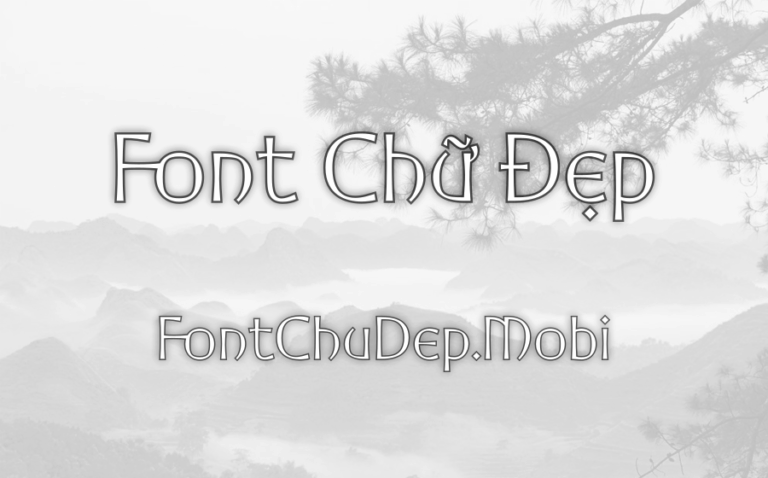
Font UVN Thời Đại 1, do nhà thiết kế tài năng Tom Trương ra mắt vào năm 2001, thực sự là một kiệt tác trong thế giới phông chữ sans-serif. Những đường nét tinh tế, rõ ràng và đầy thanh lịch của nó không chỉ đáp ứng nhu cầu dễ đọc mà còn mang đến vẻ đẹp hiện đại, cuốn hút. Là một người đam mê thiết kế, tôi hoàn toàn bị chinh phục bởi sự hỗ trợ toàn diện của UVN Thời Đại 1 với các ký tự tiếng Việt, làm cho nó trở thành lựa chọn lý tưởng cho các dự án liên quan đến văn hóa bản địa.
Không chỉ nổi bật với thiết kế gọn gàng và tối giản, UVN Thời Đại 1 còn có khả năng ứng dụng rộng rãi trong nhiều lĩnh vực khác nhau. Từ việc thể hiện sức mạnh trong các tiêu đề, văn bản, cho đến việc tạo dấu ấn riêng qua thiết kế logo, phông chữ này đều làm tốt vai trò của mình. Trong lĩnh vực truyền thông và sự kiện, UVN Thời Đại 1 khẳng định được vị thế của mình qua các hội thảo, triển lãm và sự kiện doanh nghiệp lớn, nơi mà sự chuyên nghiệp và hiện đại luôn được đặt lên hàng đầu. Hơn nữa, với ngành thiết kế đồ họa và giáo dục, phông chữ này tiếp tục phát huy điểm mạnh, trở thành công cụ hữu ích trong tay người sáng tạo.